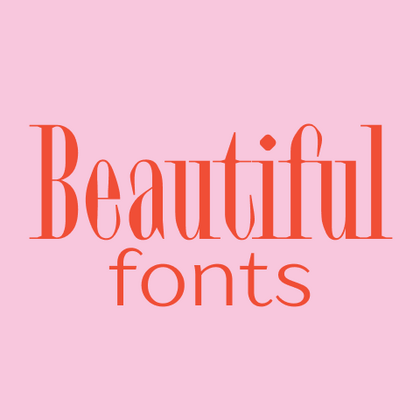
Schöne Schriftarten
Elegante Proportionen und visuelle Harmonie definieren wahrhaft schöne Schriften in der TypeType-Kollektion. Jede Schrift ist mit typografischer Perfektion gestaltet, von exquisiten kalligrafischen Stilen bis hin zu verfeinerten minimalistischen Designs. Diese schönen Schriften eignen sich für Projekte, bei denen Form genauso wichtig ist wie Inhalt — Premium-Branding, luxuriöse Verpackungen, künstlerische Publikationen und Hochzeitseinladungen. Sie balancieren Schönheit mit Funktionalität und sind nicht nur ästhetisch ansprechend, sondern auch durchdachte Werkzeuge zur Schaffung unvergesslicher visueller Identitäten.
TT Odellia ist eine altstilige Antiqua mit zeitgenössischer Formensprache, inspiriert von venezianischen Schriften und klassischer Musik.
TT Nooks Script besitzt eine eigenständige Zeichnung, für die es kaum direkte Vergleichspunkte gibt.
TT Qurdisma ist eine schmale, kompakte dekorative Schrift, die an eine eigenwillige Pflanze erinnert. Ihre geschwungenen, fließenden Konturen bilden ein pflanzliches Ornament.
TT Neoris ist eine elegante Neo-Grotesk mit unbegrenztem Potenzial — eine Schrift, die alle modernen Anforderungen und Wünsche der Nutzer vereint.
TT Supermolot Neue ist eine neu gestaltete, erweiterte und deutlich verbesserte Reinkarnation der beliebten Schriftfamilie.
TT Turns ist eine markante geometrische Sans Serif mit expressiven Elementen. Diese vielseitige Schrift eignet sich hervorragend für Fließtext und entwickelt in großen Schriftgraden einen ausgeprägten Display-Charakter.
TT Regins ist eine moderne schottische Serifenschrift. Starker Kontrast und scharfe dreieckige Serifen verleihen ihr einen strengen und kraftvollen Charakter, während raffinierte Formen, vergrößerte Kleinbuchstaben und leicht kondensierte statische Proportionen dem Design Eleganz verleihen.
TT Quaris ist eine elegante moderne Sans Serif mit hohem Kontrast, deren Design zwischen weichen und scharfen Formen balanciert. Die Glyphenformen wirken fließend und tendieren zur Rundlichkeit, besitzen jedoch zugleich markante scharfe Elemente.
TT Modernoir ist eine Display-Sans-Serif mit dynamischen Proportionen. Fließende Linien und feine Jugendstilformen verschmelzen in dieser Schrift harmonisch mit dem rhythmischen Fluss und der improvisatorischen Freiheit des Jazz.
TT Firs Neue ist eine zeitgemäße Reinkarnation der guten alten serifenlosen TT Firs.
TT Norms® Pro ist eine typografische Legende, die von weltbekannten Marken geschätzt wird. Entwickelt durch mehrere Iterationen, hat sie MyFonts erobert und typografische Vielseitigkeit neu definiert. Ein Design-Arbeitspferd, das sich von einem bescheidenen Werkzeug in einen unverzichtbaren kreativen Begleiter verwandelt.
TT Commons™ Pro ist das typografische Kraftpaket des Studios. Eine Schriftart, die so vielseitig ist, dass sie sich einer Kategorisierung entzieht und Stil und Funktion nahtlos verbindet. Für Designer, die eine universelle Grundlage suchen, die jedes Projekt aufwertet, ist dies die endgültige Wahl.
TT Hoves Pro ist eine skandinavische serifenlose Schrift, die minimalistische Eleganz versprüht. Sie ist die Geheimwaffe eines Designers, der komplexe Herausforderungen mit müheloser Präzision in visuelle Poesie umwandelt, und dabei gleichzeitig dezent und unverwechselbar.
TT Supermolot Neue verändert die visuelle Kommunikation grundlegend! Eine fortschrittliche, modulare serifenlose Schrift, die den Puls der technologischen Innovation einfängt und eine elektrisierende Vision für alles von immersiven Spieloberflächen bis hin zu kühnen visuellen Erzählungen bietet.
TT Firs Neue ist eine ausgewogene serifenlose Schrift, die von der skandinavischen Designphilosophie geprägt ist. Elegant und vielseitig, poliert durch zwei bewusste Überarbeitungen, um typografische Perfektion zu erreichen.
TT Rounds Neue ist eine weiche und freundliche Schrift, die es versteht, anders zu sein. In leichteren Schriftschnitten wirkt sie minimalistisch und neutral. In den fetten Schriftschnitten bläht sie sich auf und erreicht maximale Rundheit, die kindlichen Charme ausstrahlt.
TT Fors ist ein Schweizer Taschenmesser der Typografie. Diese geometrische serifenlose Schrift ist durch ihre klaren, raffinierten Proportionen vielseitig einsetzbar. Sie kann zur Definition von Schnittstellen oder zur Gestaltung von visuellen Akzenten verwendet werden.
TT Paplane ist eine kantig wirkende Display-Sans-Serif.
TT Cometus ist eine ausdrucksstarke Schrift, die vom ersten Moment an fesselt.
TT Octosquares ist eine frische, überarbeitete, erweiterte und deutlich verbesserte Version unserer ersten kommerziellen Schrift TT Squares und ihrer schmalen Variante.
TT Carvist ist eigenwillig, verspielt und mutig — eine Schrift, die Aufmerksamkeit hervorragend auf sich zieht.